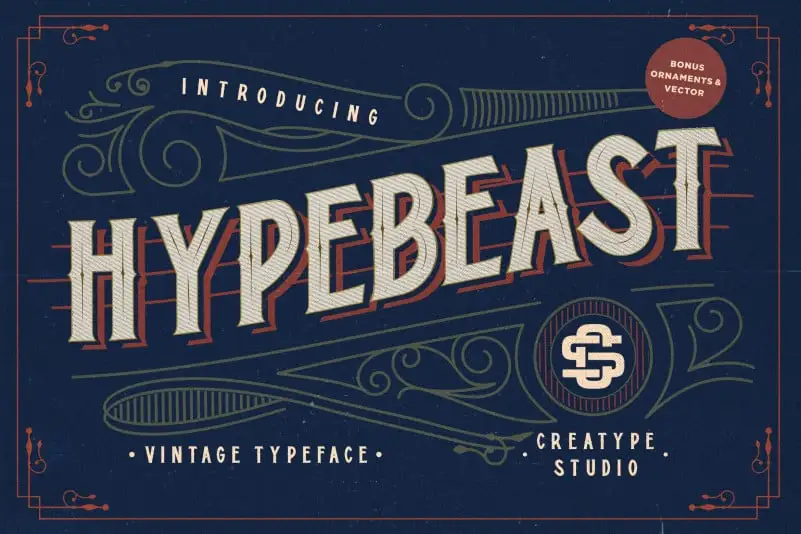
Hypebeast – Layered & Vintage Font – Download Grátis
A Hypebeast – Layered & Vintage Font é uma nova tipografia multifacetada que inspira-se nos selos antigos. Essencial para quem está buscando fazer algo realmente único, essa fonte oferece um toque vintage com elementos decorativos e robustos. Inspirada nas letras de sinalização e arte do passado, ela combina a elegância clássica com uma leveza que resulta em letras semelhantes às antigas. A adição do elemento vectorial “Adventure & Camp” oferece ainda mais opções para criar uma atmosfera vintage, seja no título de um produto, na embalagem ou até mesmo nas logos de cervejas. Essa fonte é perfeita para quem busca uma conexão com o passado enquanto mantém a contemporaneidade e criatividade. Com sua ornamentação elegante inspirada em letras do passado, Hypebeast – Layered & Vintage Font é uma excelente escolha para qualquer projeto de gráficos que valorize tanto o estilo vintage quanto a modernidade. Seja você um designer gráfico experiente ou alguém novato na área, essa fonte oferece as ferramentas necessárias para transformar seus projetos em verdadeiros trabalhos de arte, recriando atmosferas nostálgicas e frescas ao mesmo tempo.